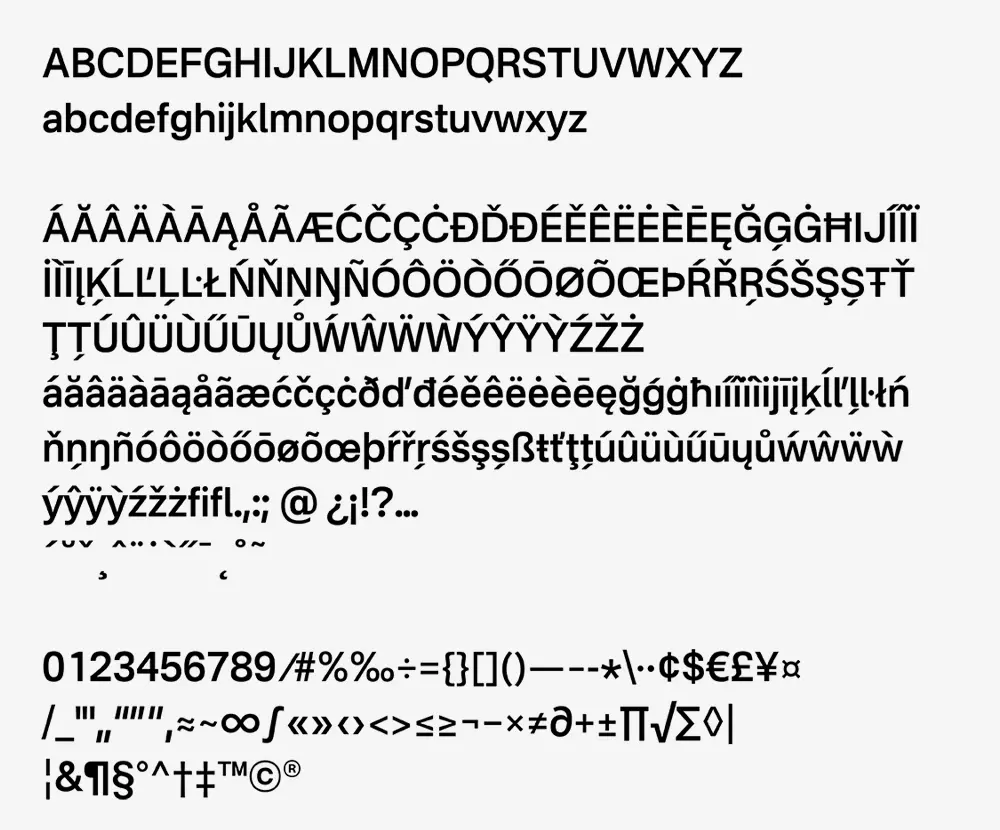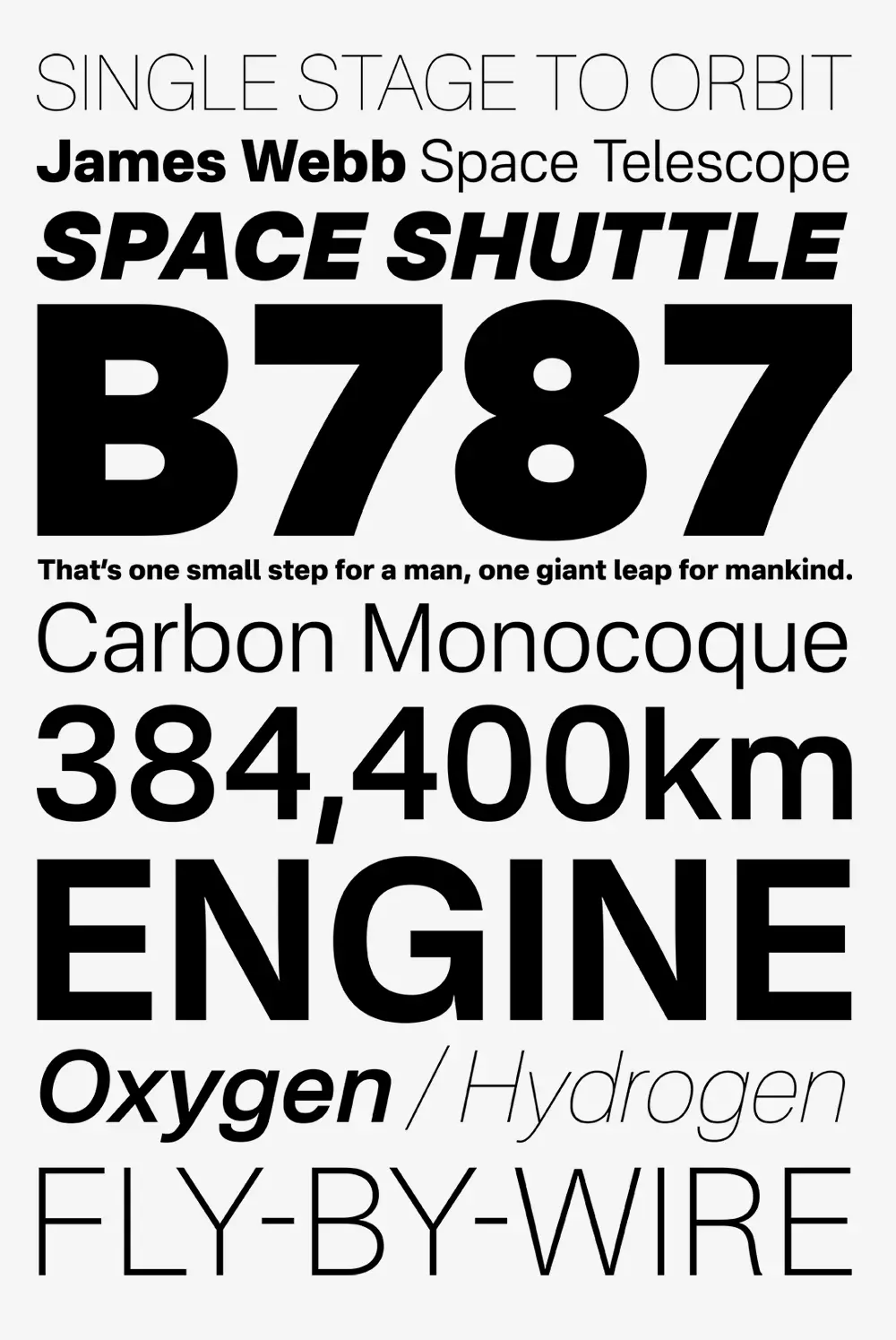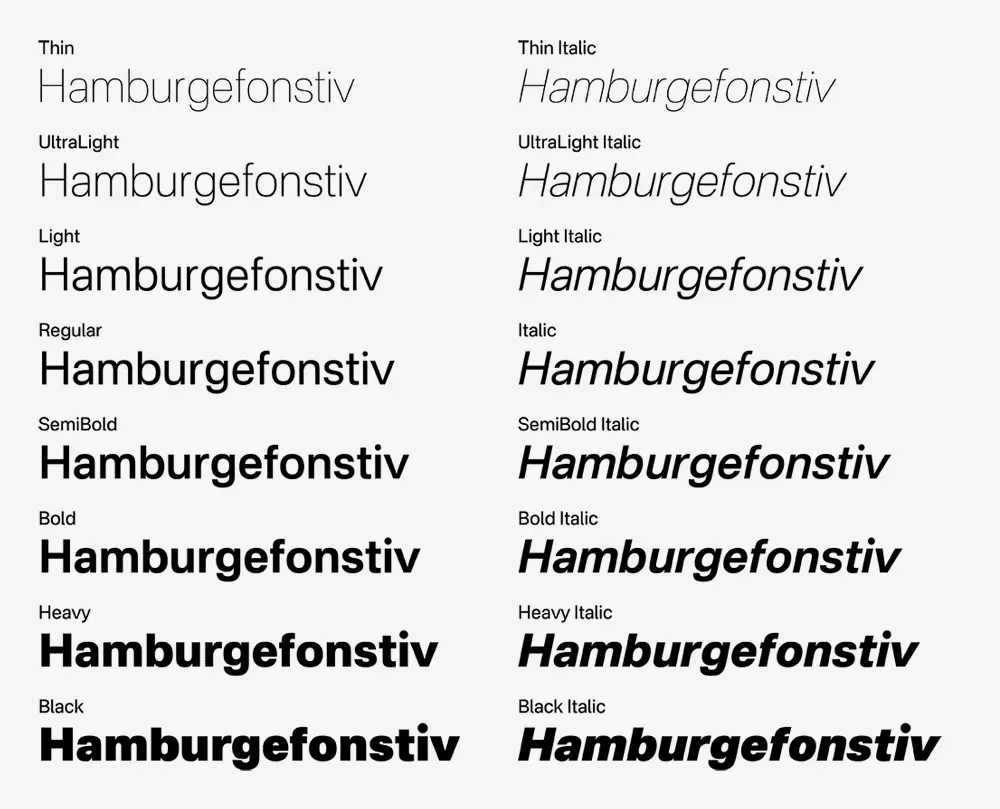
Nacelle預覽
Nacelle介紹
Nacelle 是一種新怪誕的無襯線字體,是在 Aileron 的基礎上重新設計和徹底翻新的。在保留 Aileron 的基本概念“創建一個在用戶界面上易於看到和識別的新怪誕”的同時,我們調整了指標和細節以創建更自然的形狀。
NacelleはAileronのデザインを見直し、全體的に改修を施したネオグロテスク・サンセリフです。Aileronの「UI上で見やすい・識別しやすいネオグロテスクを作る」という基本コンセプトはそのままに、メトリクスや細部を調整し、より自然な形に仕上げました。